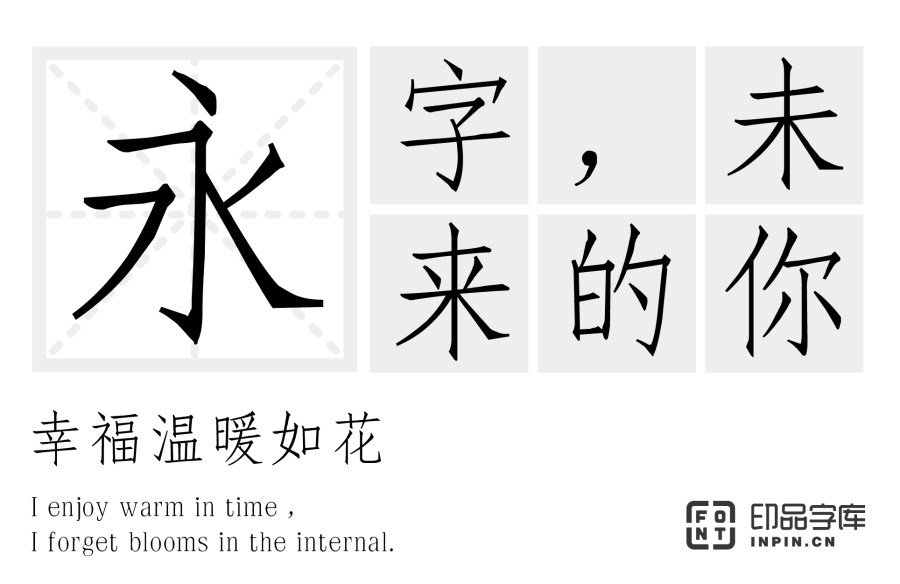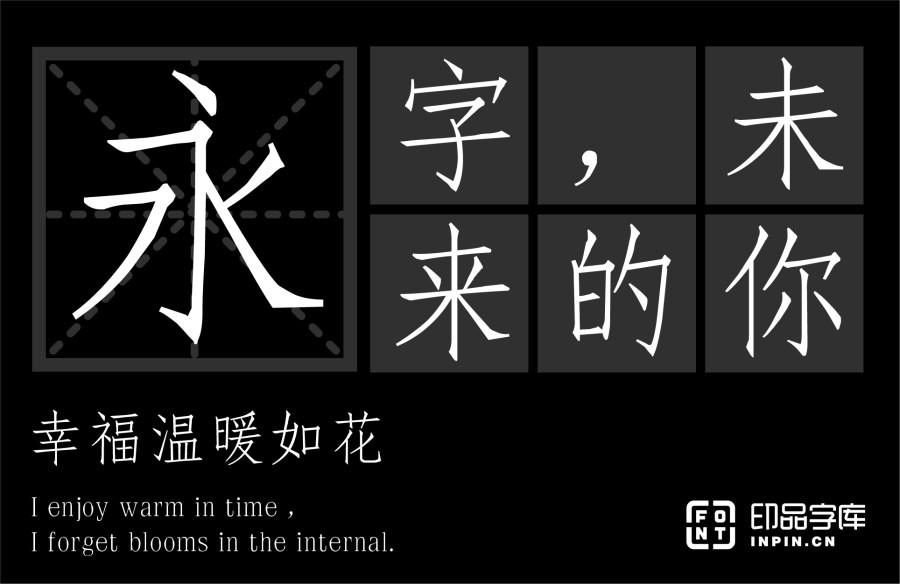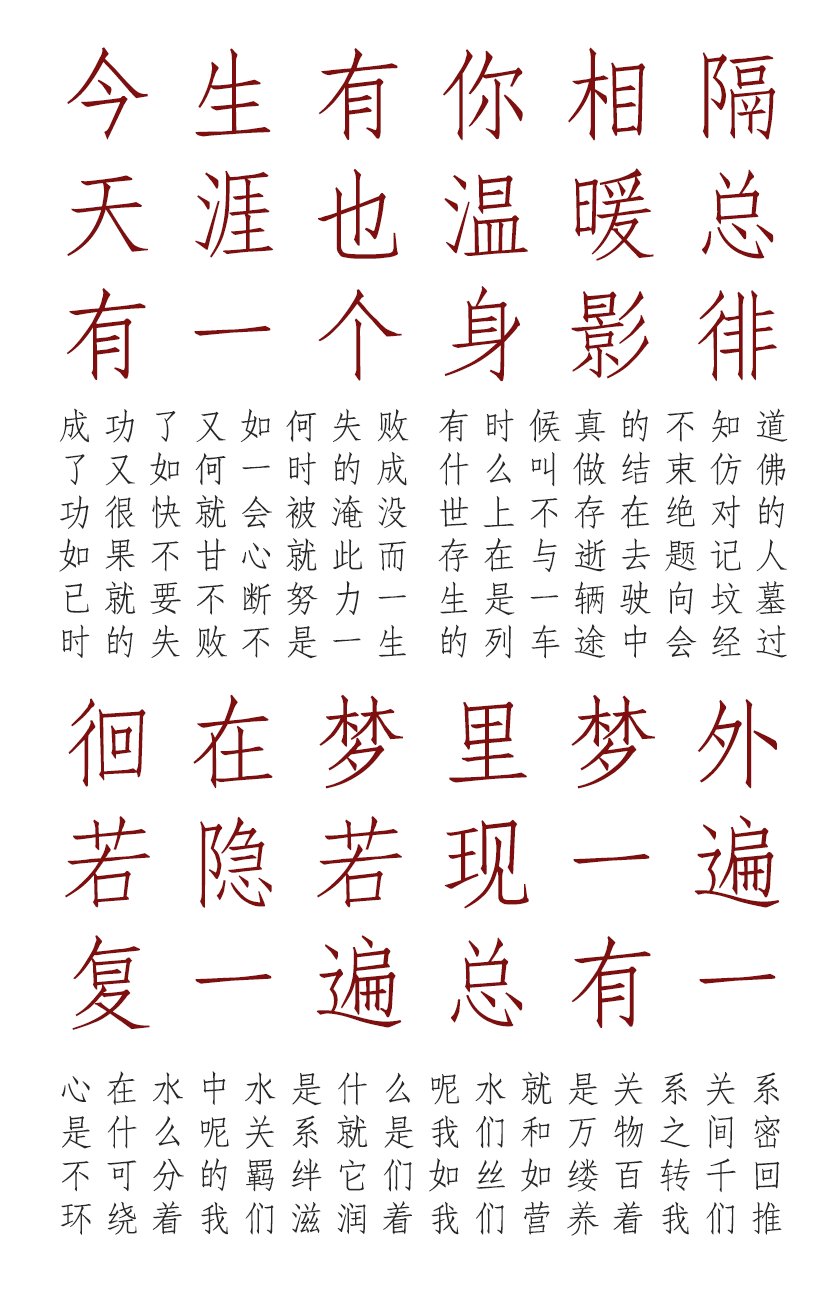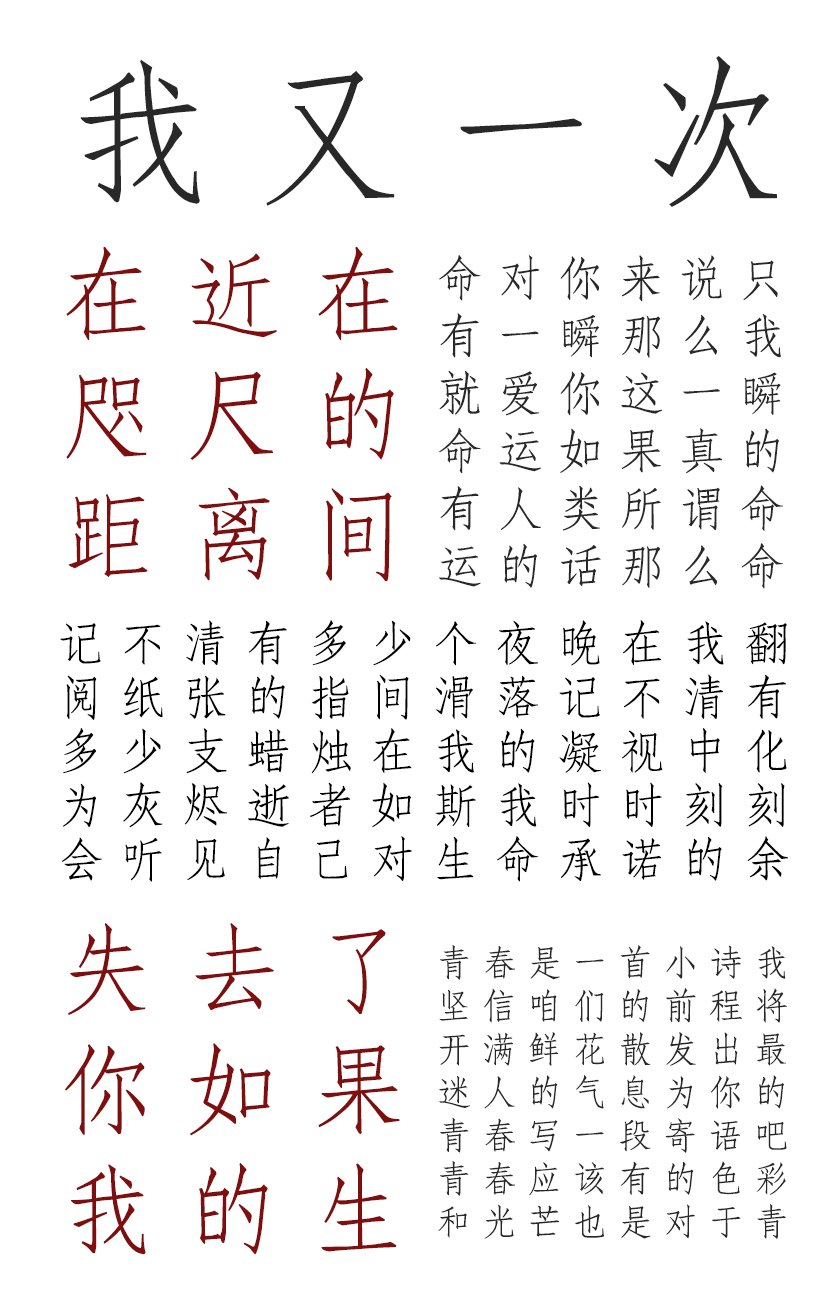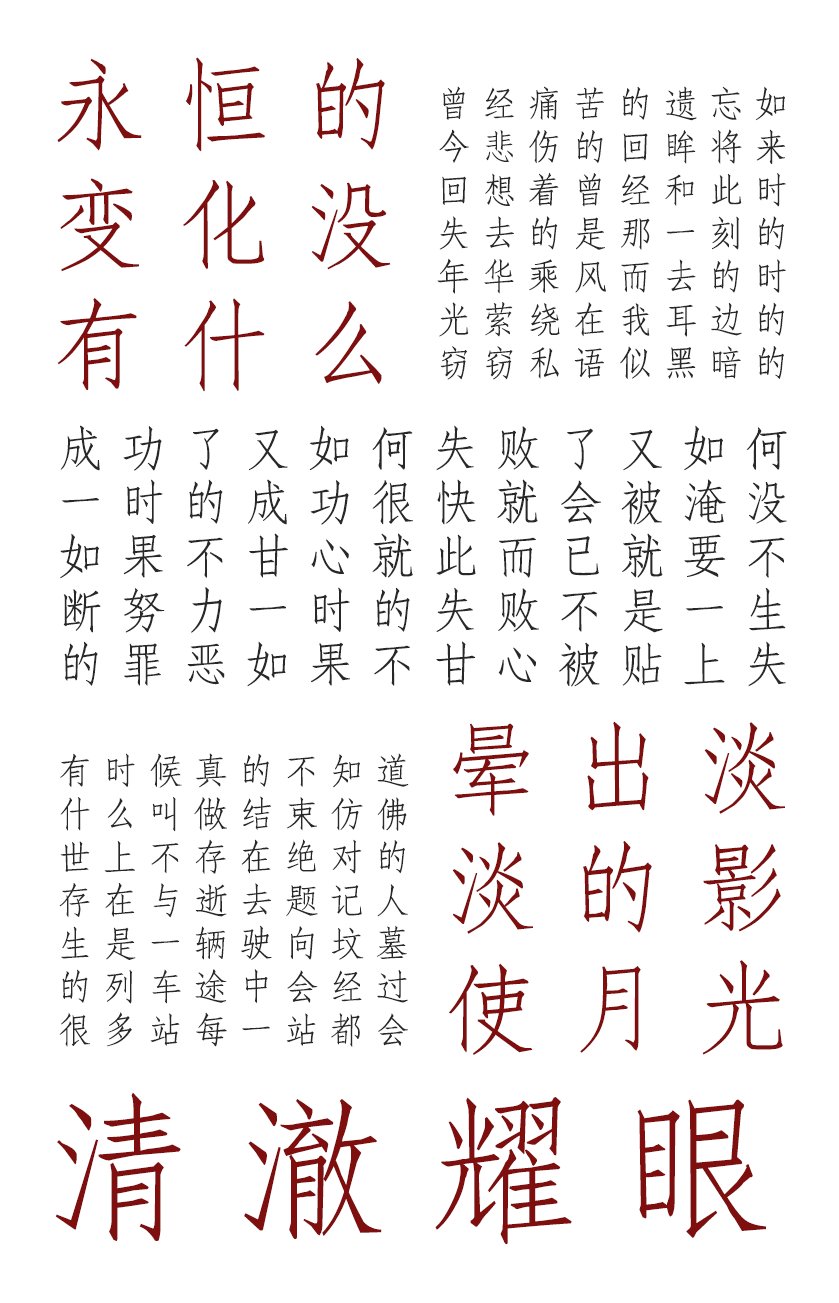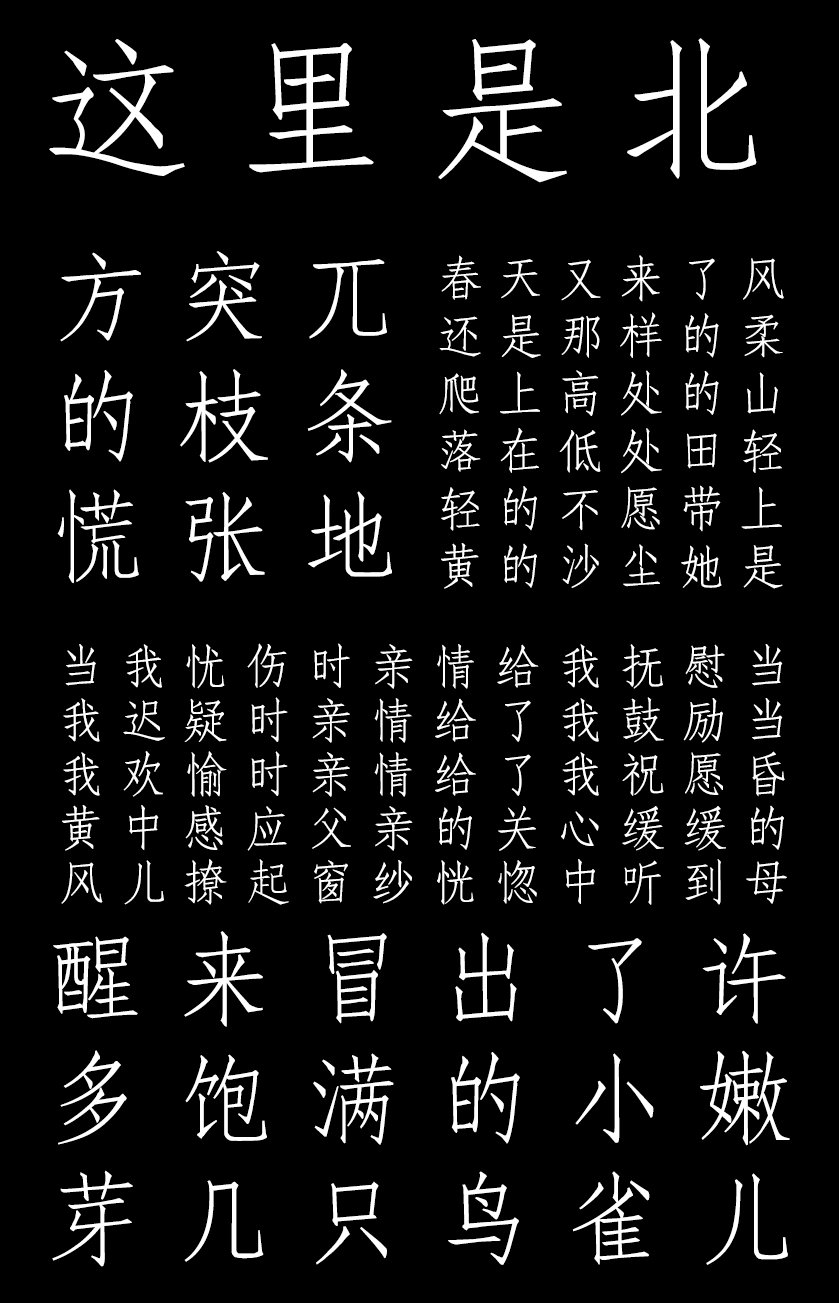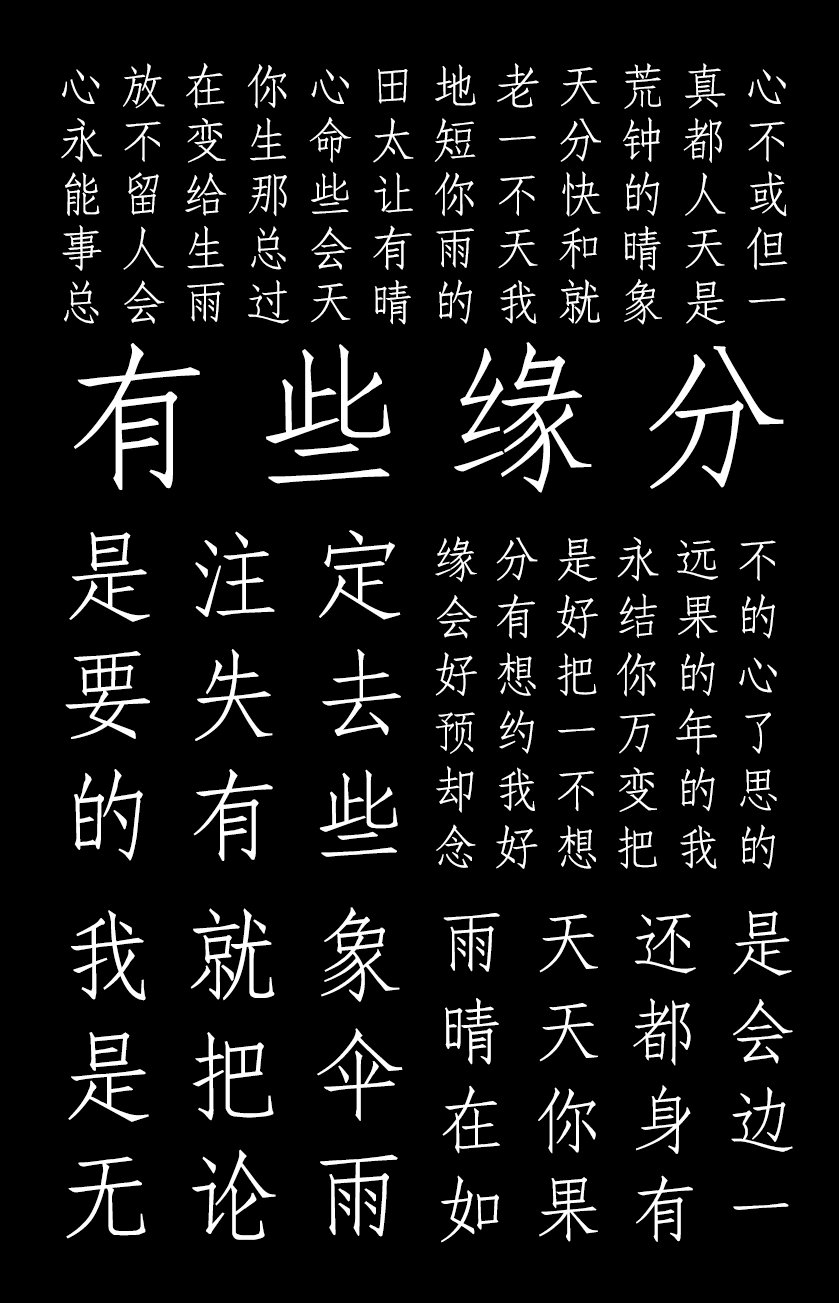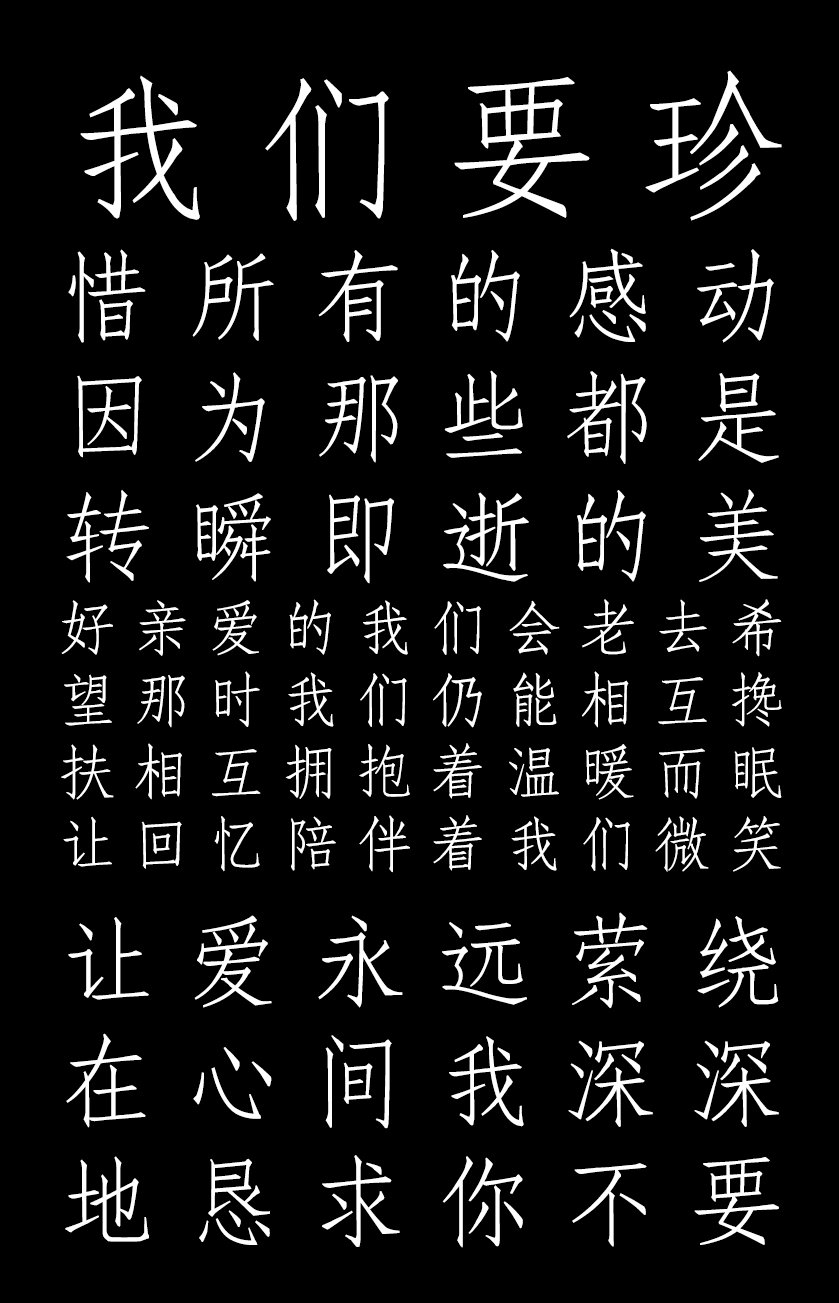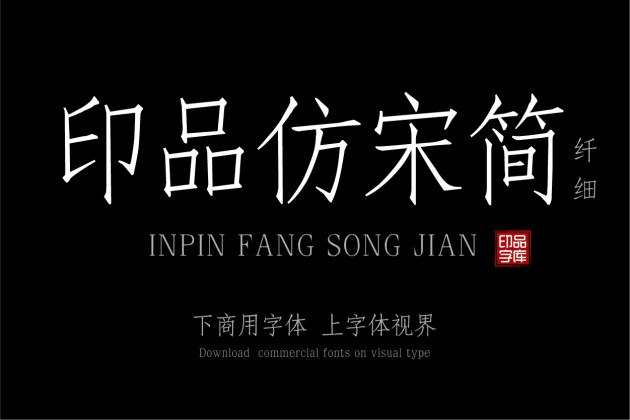
印品仿宋简 纤细
仿宋是仿照宋代的风格而制,但也不是完全仿照宋代某个文士、书法家、名人的字体。仿宋是印刷字体的一种,印品仿宋简是参考宋版书的雕版字体灵感创作而来,适用于排印副标题......
• 印品仿宋简的创作灵感源于宋体,却又不似宋体般横细竖粗,其各笔画等粗,无太大的差别,起笔和落笔成倾斜形,笔法锐利,结构紧密,笔画秀丽,清秀美观。 印品仿宋简采用宋体结构、楷书笔画,字体较为瘦长平滑,略带棱角,笔画收、尾和转折处常有粗重尖耸的三角形锋角,浑厚凝重,每个单字大多是一个平衡的结构体系,字心聚集,是一种较为规范的雕版字体。 印品仿宋简是一种较为清秀的字体,笔画横竖粗细均匀,书写方便快捷,是印刷字体的一种,适用于排印副标题、诗词短文、批注、引文等,在一些读物中也用来排印正文部分。